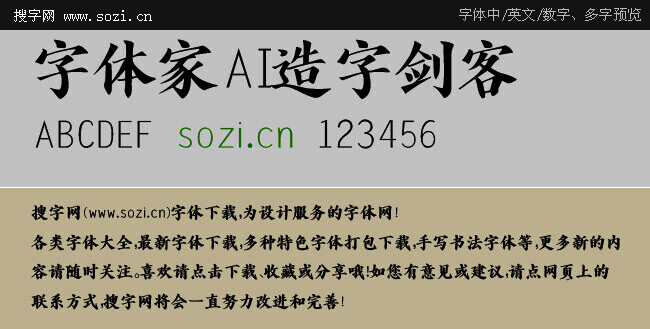
字體家AI造字劍客
搜字網(wǎng)提供一款字體家AI造字劍客中文書法字體下載,字體家AI造字劍客是一款A(yù)I字體作品,該字體是一款榜書風(fēng)格字體,運筆雄厚渾然天成的書法線條體現(xiàn)具有力量感和自然流暢的書法風(fēng)格。通過這種書法線條展現(xiàn)產(chǎn)品氣韻和風(fēng)采。適合圖書設(shè)計、包裝設(shè)計、海報設(shè)計等應(yīng)用。